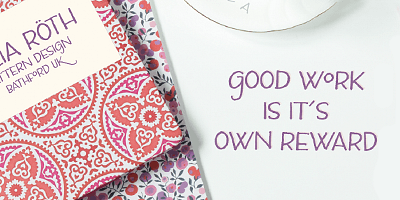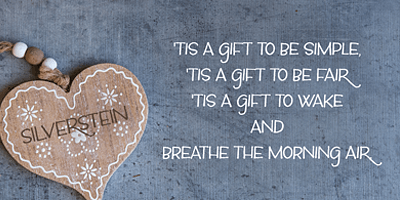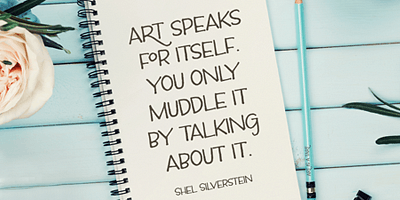
Silverstein ist eine moderne, einfache Großbuchstaben-Schriftart. Die Zeichen sind eine Anspielung auf architektonische Schriftzüge und stammen aus den früheren Tagen des Designers, als er bis in die Abendstunden Grundrisse und Präsentationszeichnungen entwarf.